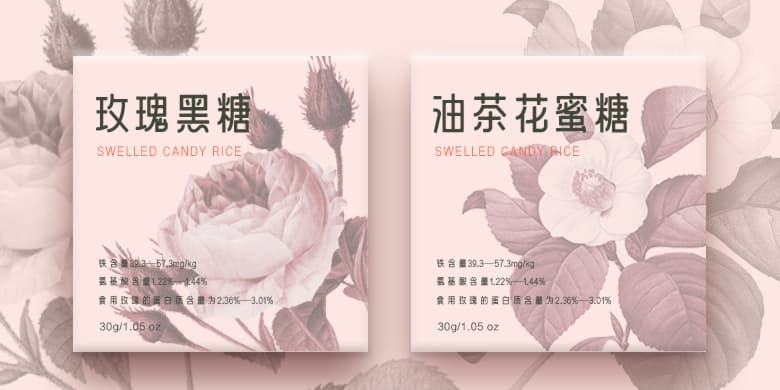
润黑是以黑体字形结合部分圆体的特征进行重新设计的新形式字体,在保留了传统黑体的细节笔画特点,同时笔画细节末端比黑体更润,笔画中的撇相较黑体弧度更大,捺更为笔直。字体灰度匀称,细节饱满。独特的表现形式让字体在商业应用中更加灵活和广泛,能够适合多种的商业场景,让一个字体具有它的多面性,表现出它不一样的字体性格。本款字形适用于个性类适合品牌标志、招牌、包装、广告、游戏、设计等众多场景应用。